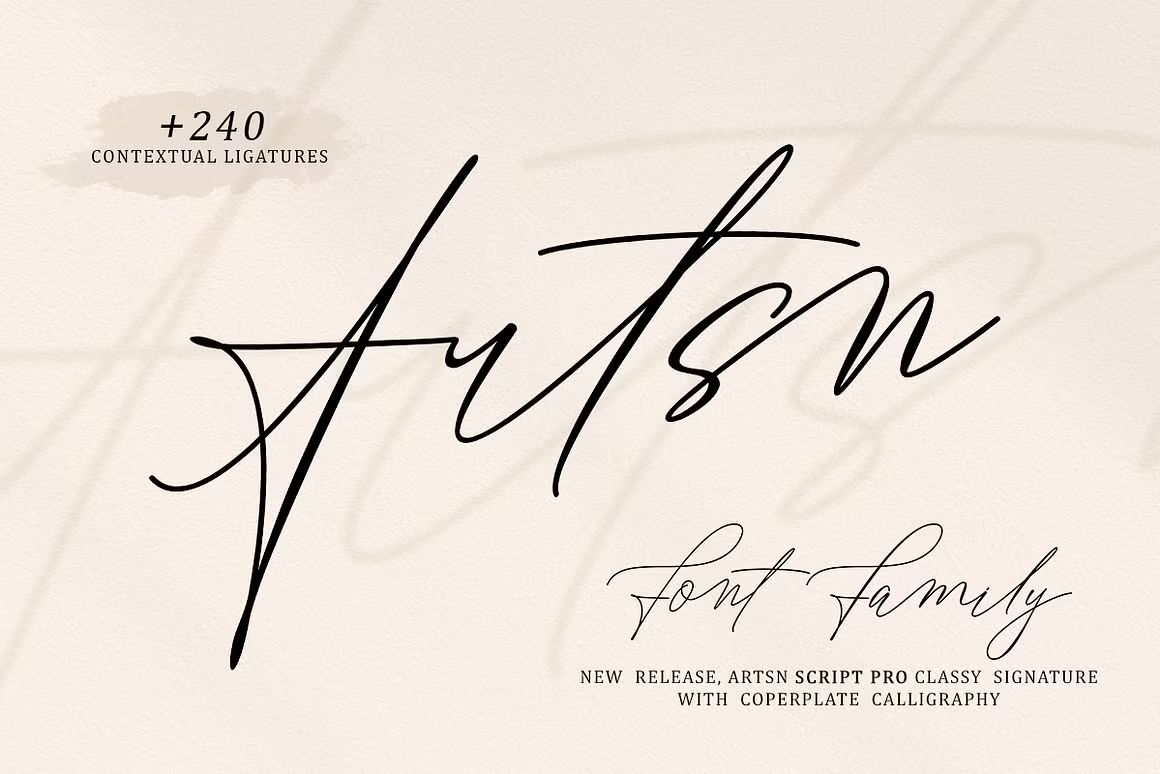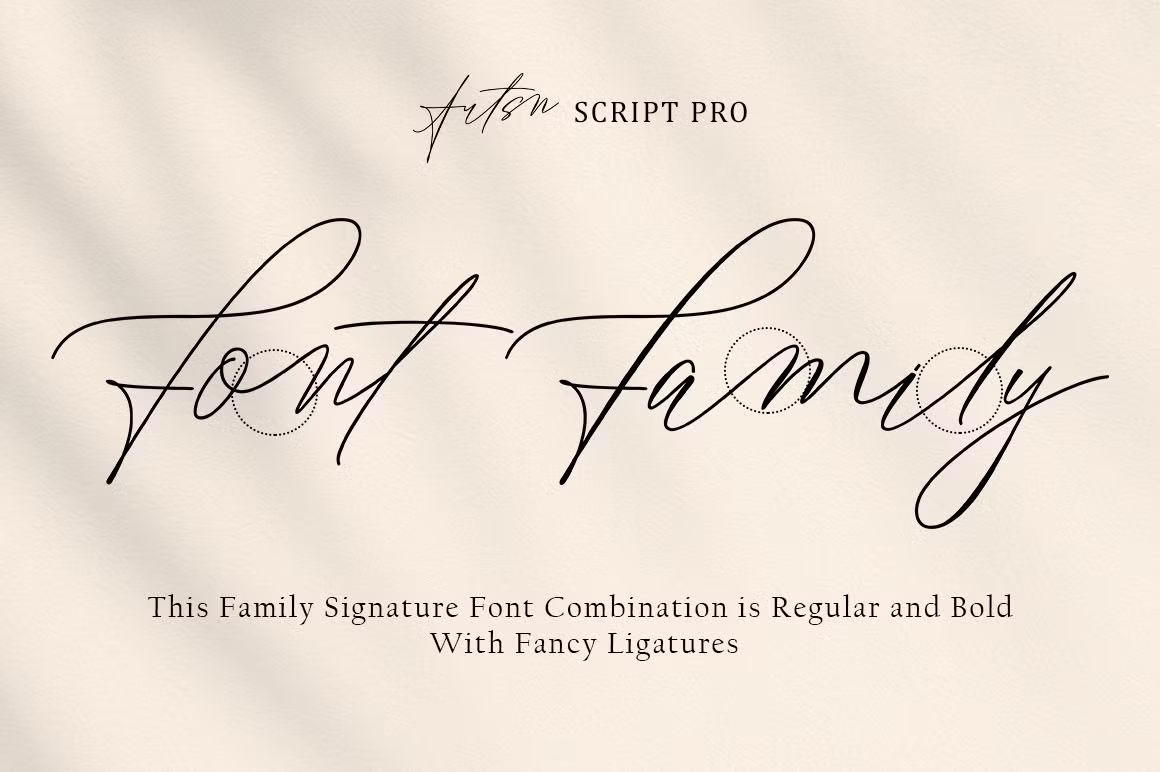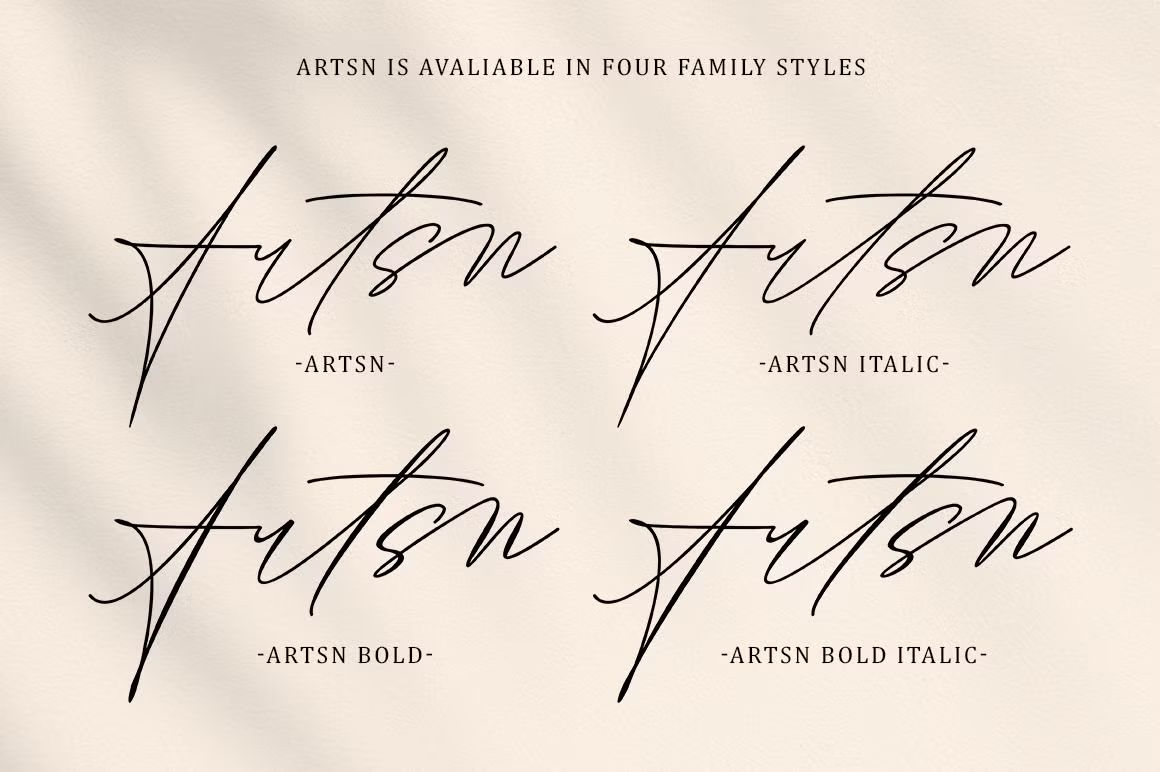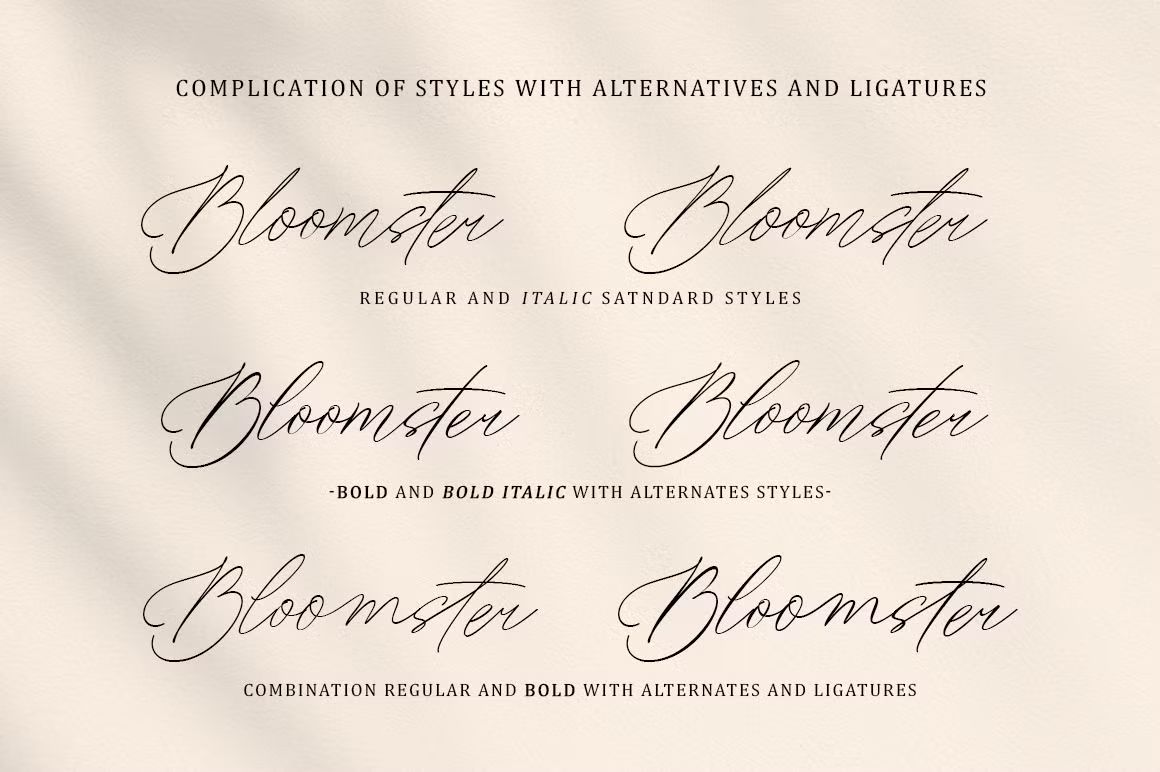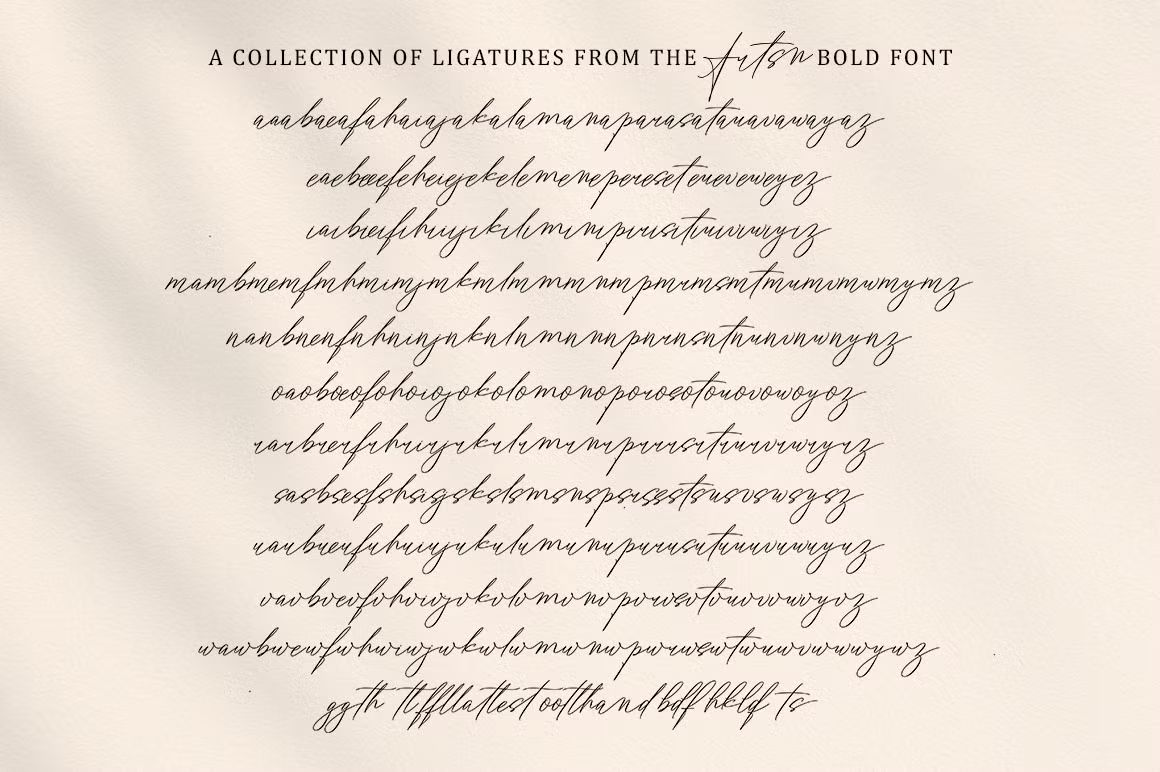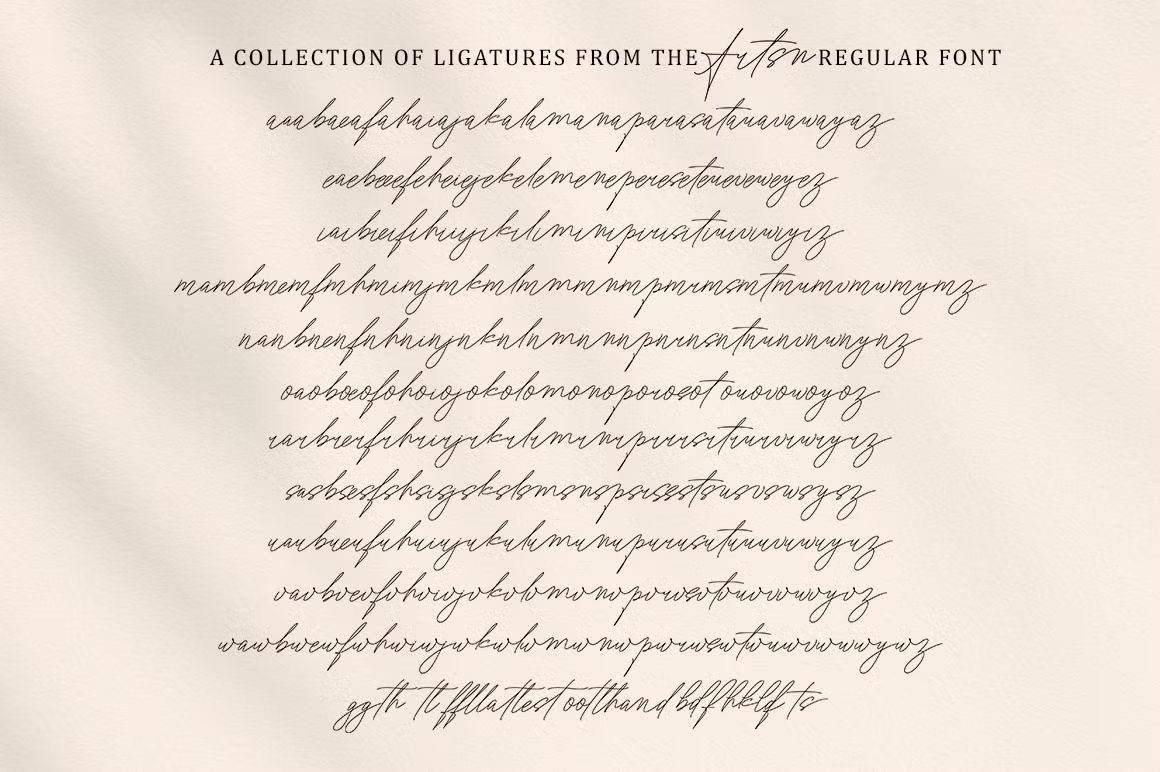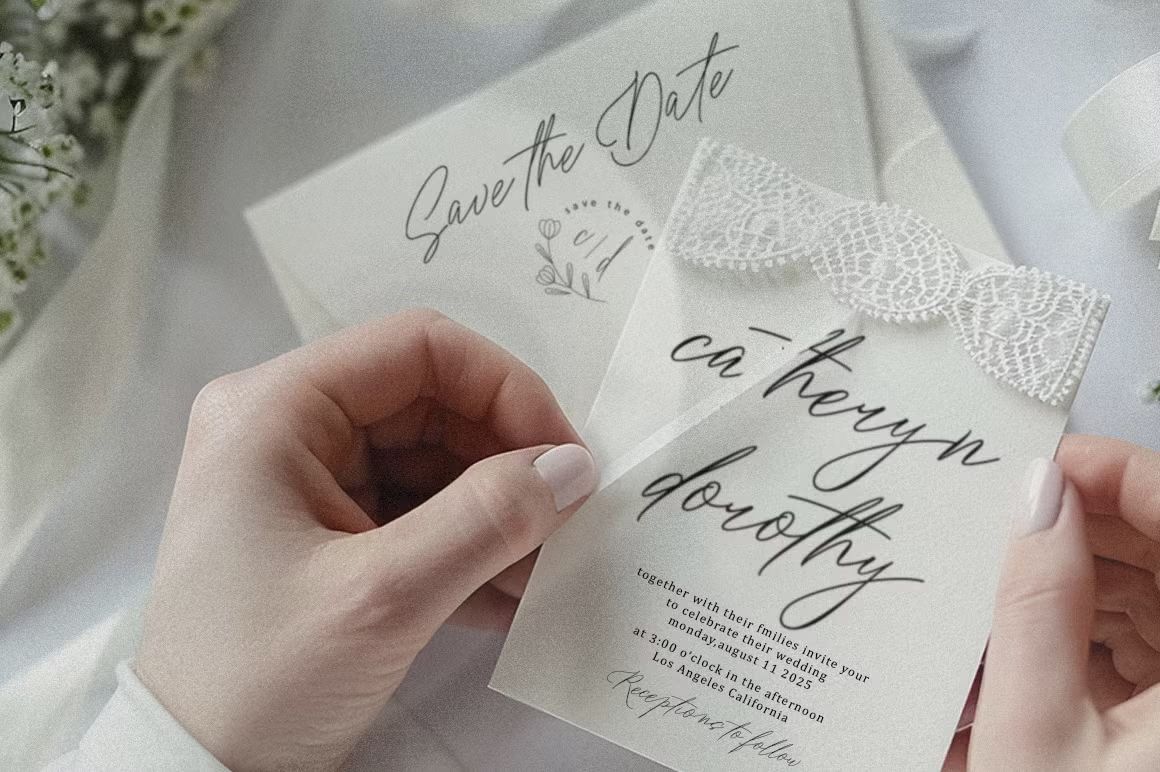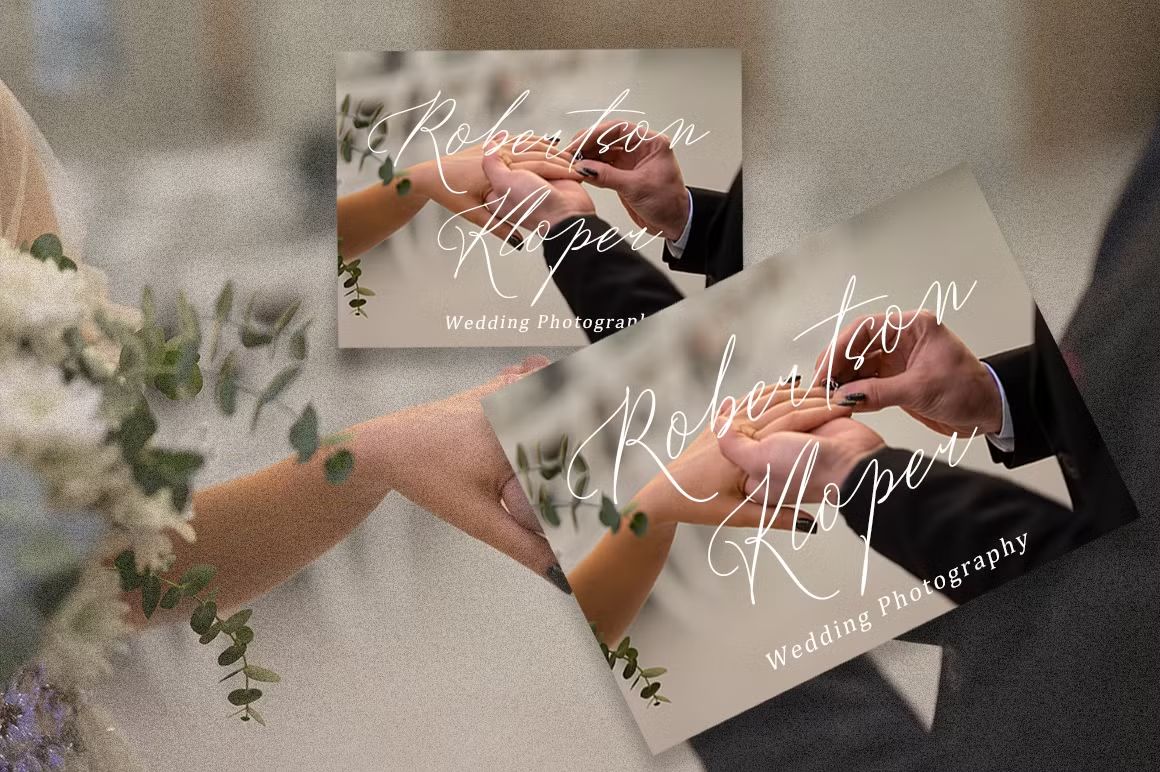
Artsn – Script Pro Font
Artsn adalah font script profesional dengan gaya tulisan tangan yang stylish dan dinamis, ideal untuk branding, logo, undangan, dan desain kreatif yang membutuhkan tampilan elegan namun modern.
Artnsn adalah font script pro dengan desain elegan dan dinamis, memberikan kesan modern dan artistik pada setiap karya. Dengan garis-garis halus dan bentuk yang mengalir, font ini cocok untuk berbagai kebutuhan desain seperti branding, logo, undangan, kartu nama, dan proyek kreatif lainnya. Artsn memberikan nuansa yang berkelas namun tetap penuh karakter.
Fitur unggulan:
• Gaya script tulisan tangan yang elegan dan modern
• Cocok untuk branding, logo, undangan, dan desain kreatif lainnya
• Termasuk huruf besar, huruf kecil, angka, dan simbol lengkap
• Ideal untuk proyek cetak dan digital yang membutuhkan tampilan mewah dan artistik